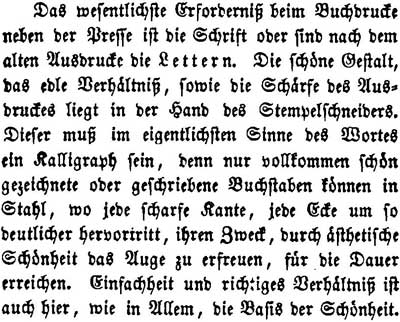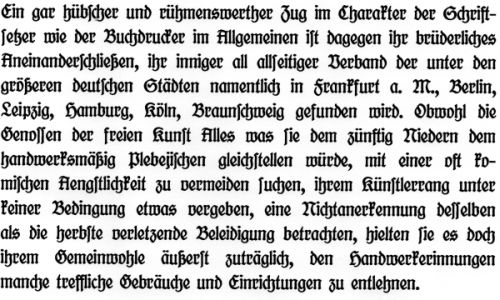
Typografie-Zitate
»Ein wirklich gut gemachtes Buch ist nur von einer Elite als solches erkennbar; die übergroße Mehrzahl der Leser empfindet seine exzeptionelle Qualität nur dumpf. Ein wirklich schönes Buch darf äußerlich ›nichts Besonderes‹, sondern soll ›nur‹ vollkommen sein.«
Jan Tschichold, 1946
»So wie Gutenberg die bibelschreibenden Mönche arbeitslos
machte, so bringen die computergesteuerten Satz- und Umbruch-
systeme die Jünger Gutenbergs um ihren Beruf. Das Pendel
schlägt jetzt heftig nach einer Seite aus. Aber es wird auch wieder
zurückschwingen, und dann wird man bemerken, daß doch nicht
jeder Beliebige ohne Ausbildung mit Schrift umgehen kann.«
Norbert Denkel in der Wochenzeitung
»Die Zeit«, 31. März 1978
»Personen, die Texte für den Bildschirm – übrigens auch für Print – aufbereiten,
sind sich selten bewusst, wie man optimale Leserlichkeit erreicht. Dabei ist dies
uraltes Wissen. Wenn im 18. Jahrhundert die Buchstaben einer Blei­schrift gegossen
wurden, skalierte man nicht einfach auf verschiedene Grössen. Die Garamond war
für 20 Punkt anders geschnitten als für 6 Punkt, die grössere Buchstabenabstände
aufwies. Die Laufweitenkorrektur wurde ganz automatisch berücksichtigt
Ralf Turtschi
im Gespräch mit Matthias Schüssler (Tages-Anzeiger, Zürich)
»Nicht nur Schriftsetzer und Büroboten braucht heute keiner mehr.
Auch ein Dienstwagen ist nicht zwingend notwendig, um eine gute Zeitung zu machen.«
Die Basler Zeitung am 04. 10. 2014 über die FAZ
»Zum Druck wurde eine schöne deutliche Schrift verwendet,
denn die meisten Leser dieses Buches werden genöthigt sein,
es in später Abendstunde nach Beendigung ihrer Arbeitzu lesen;
möge es ihnen dann auch eben solches Interesse und die Erhebung
bereiten, welche dem Verfasser seine gewiss nicht leichte Arbeit
versüsst haben.«
Karl Faulmann in der Einleitung seines Werkes
»Illustrierte Geschichte der Buchdruckerkunst«
Wien, Pest, Leipzig, 1882
Sensationelle Erkenntnisse :hammer:
von Jürgen Nawatzki in der „Huffington Post“
(4. November 2014)
»Der Beruf des Schriftsetzers hat sich in den letzten 30 Jahren
komplett verändert. Der moderne „Schriftsetzer“ hat heute in der Regel
einen Computerarbeitsplatz.«
Galt das nicht eigentlich schon für Monotype-Setzer? Sie gaben den Satz, statt physisch nach den Lettern zu greifen an einer Tastatur ein, die dann auf einem Datenträger gespeichert wurde.
Ist das nicht eigentlich schon recht dicht an dem, was wir heute machen, setzen wir einen Text am PC?
»Es kann vorkommen, daß ein tadellos gekleideter Herr einem schnittigen Wagen entsteigt und dann aus seiner eleganten Brieftasche eine Geschäftskarte nimmt, auf der eine ganze Serie von Setzersünden verewigt ist. Wenn er Glück hat, ist er ahnungslos; manchmal ist er aber auch der Veranlasser gewesen, der die Karte so gewollt hat.«
»Heute ist es allerdings so, daß eine Druckereileitung weit eher bereit ist, sich einen erstklassigen Wirtschafts- und Steuerberater zu verpflichten als einen tüchtigen Fachmann, der über die Typographie zu wachen hat. Natürlich weiß man, daß zwischen Qualität und Rentabilität ein enger Zusammenhang besteht, doch man ist vielfach geneigt, unter Qualität nur technische Vorzüge zu verstehen. Man vergißt, daß Qualität sich vor allem in der geistigen Substanz ausdrückt, wie denn auch die beste Kleidung und der teuerste Schmuck nicht über die geistige Leere eines Gesichtes hinwegzutäuschen vermag.«
Willi Mengel
Formprobleme der gegenwärtigen Typographie
Deutscher Typokreis e.V.
Frankfurt am Main
1955
»Es ist wohl unnötig zu betonen, daß der größte Teil der Kundschaft aus wohlmeinenden, gesitteten Menschen besteht, die sich vom Schneider und vom Friseur, vom Architekten und deshalb wohl auch vom Buchdrucker willig beraten und beeinflussen lassen. Ja, es kann so weit kommen, daß eine Druckerei eine moderne Haltung in Stilfragen einnimmt und in den Ruf kommt, nur Gutes zu liefern, und der Kunde unterwirft sich dann willig den Vorschriften, die von der Druckerei kommen. (...) Es wird (...) den Beteiligten schon aufgefallen sein, daß, wenn eine Druckerei die Typographie als Macht handhabt, alles viel besser und reibungsloser verläuft, die Zufriedenheit größer und der wirtschaftliche Erfolg gesicherter werden.«
Willi Mengel
Formprobleme der gegenwärtigen Typographie
Deutscher Typokreis e.V.
Frankfurt am Main
1955
Adolf Loos
Aus dem Text »Buchdrucker« von 1898:
»Als die Menschen noch zartere Augen hatten, da verlangte man auch, daß man im Lesen und Denken nicht durch schlechten Druck und schlechtes Papier gequält würde. Man gab dem Buch nach rechts, links und unten eine angemessene Breite weißen Papiers, damit die Finger, mit denen man das Buch gefaßt hatte, sich in entsprechender Entfernung aufhielten. Heute muß man mitten in den Druck hineintappen.«
»Anmerkungen von Adolf Loos, 1931:
Jetzt, 1931, ist man schon viel weiter! Überall werden bücher gedruckt, die den breiten weißen rand innen im bund haben, was ganz sinnlos ist. Die buchstaben aber sitzen außen ganz am rande an, je selbst die bilder stehen dort. Man kann sie nicht sehen, weil man den daumen darauflegen muß. Von den konstruktivisten bis zur Wiener Werkstätte eine front.
«
Adolf Loos
Gesammelte Schriften
Wien, 2010
ich suche ein Zitat, dass ich auf der Veranstaltung zur Einführung der Peter Schmidt Type gehört habe. Leider war die Folie zu schnell weg, als dass ich sie habe photographieren oder den Namen entziffern können. Ein Mensch, dessen Name irgendwie wie Knickeberg lautet, hat den Stoßseufzer geäußert: Wenn doch die Welt von der Idee zu heilen wäre, dass gotisch deutsch sei.
Habt Ihr eine Idee, wer das tatsächlich war und in welchem Kontext das Zitat stand?